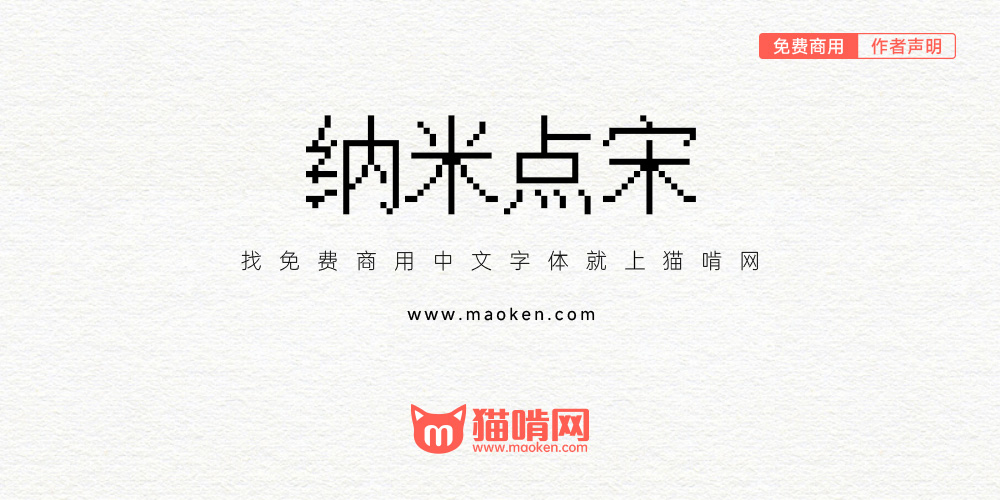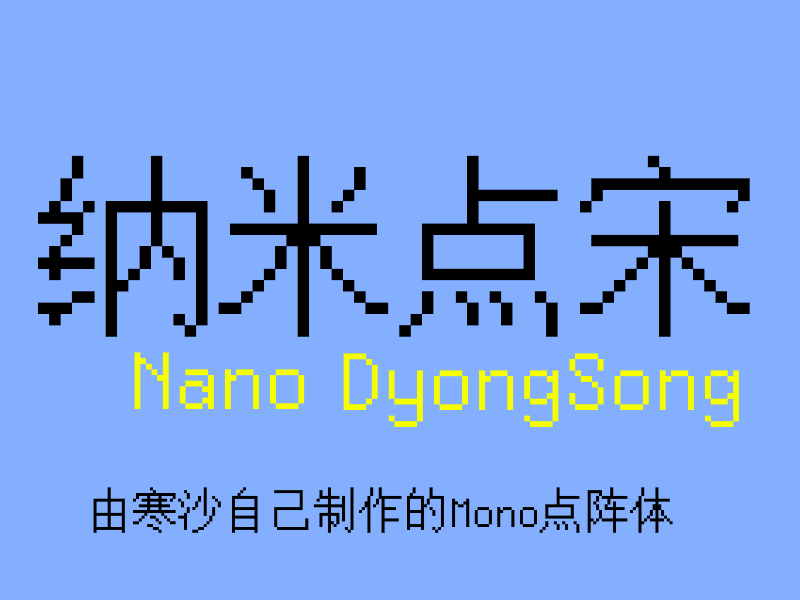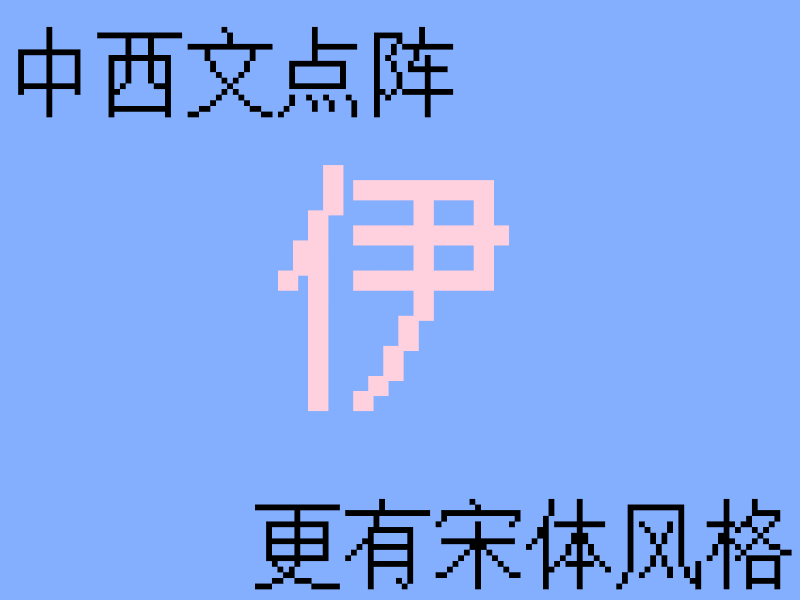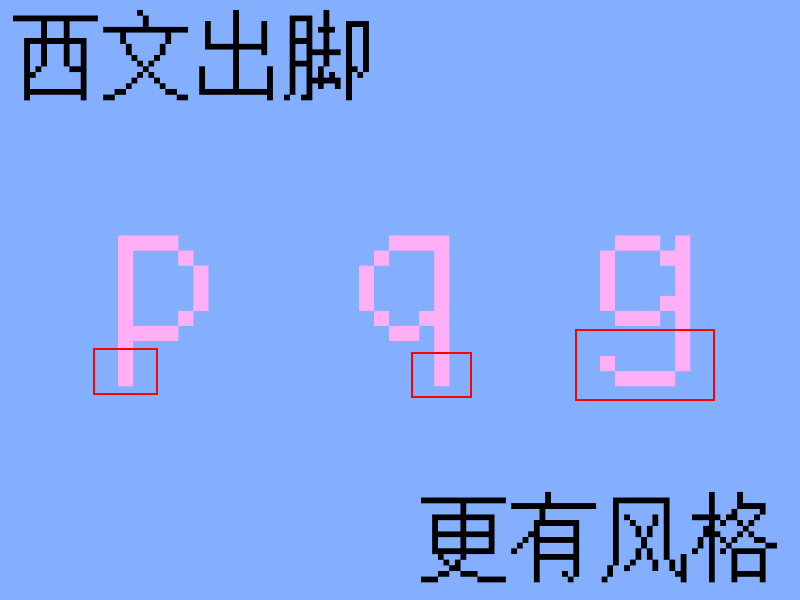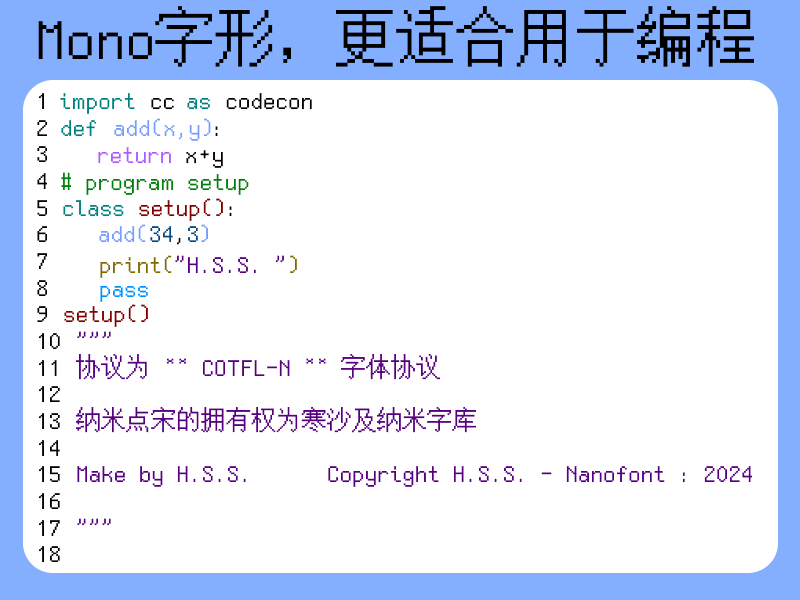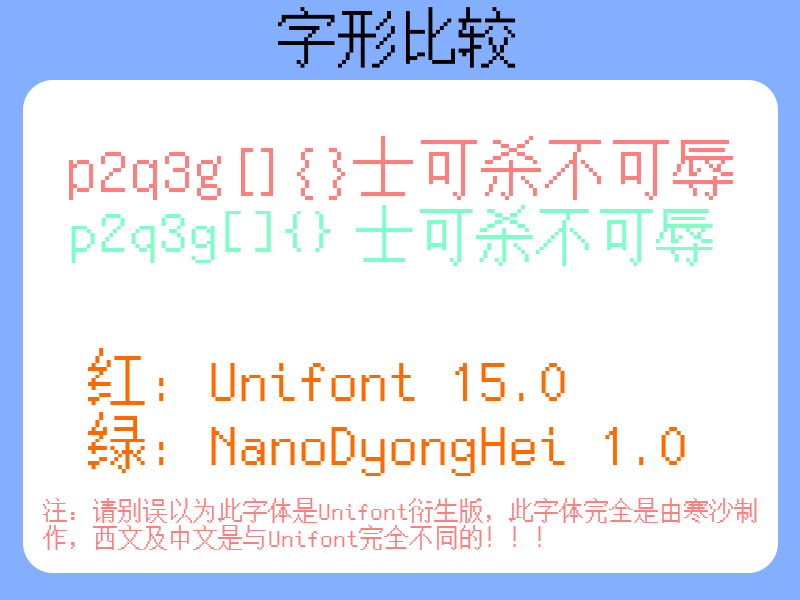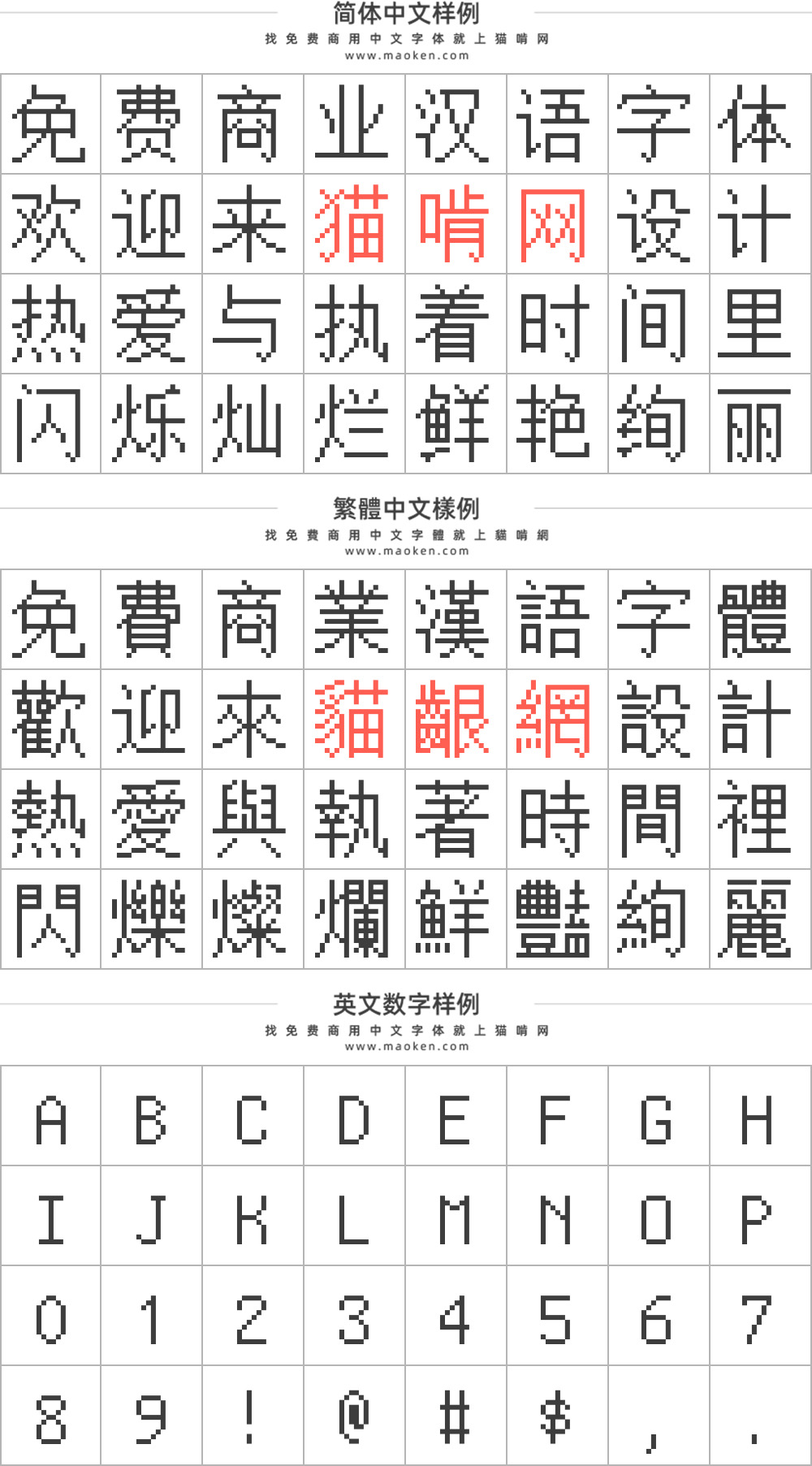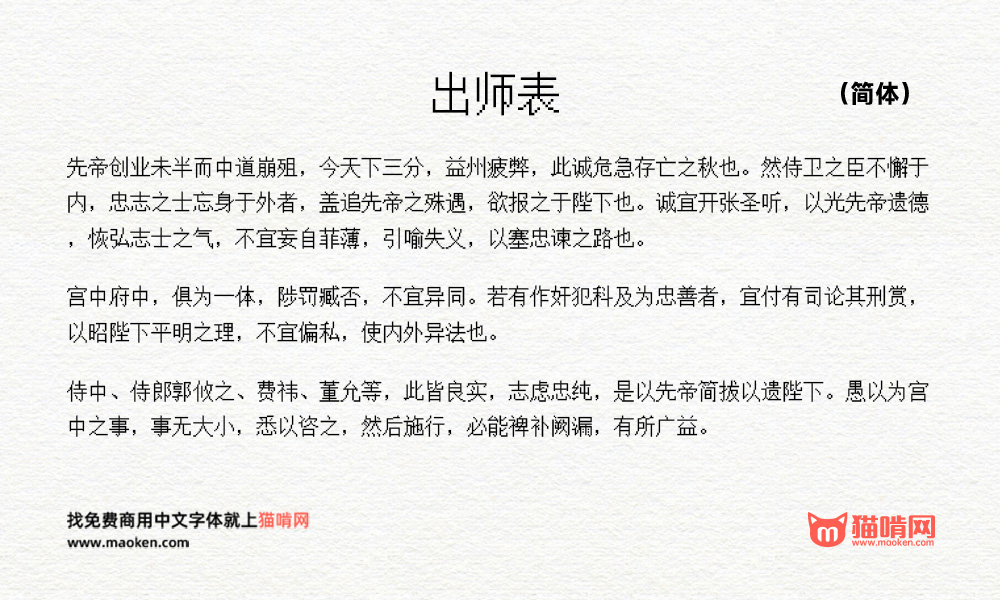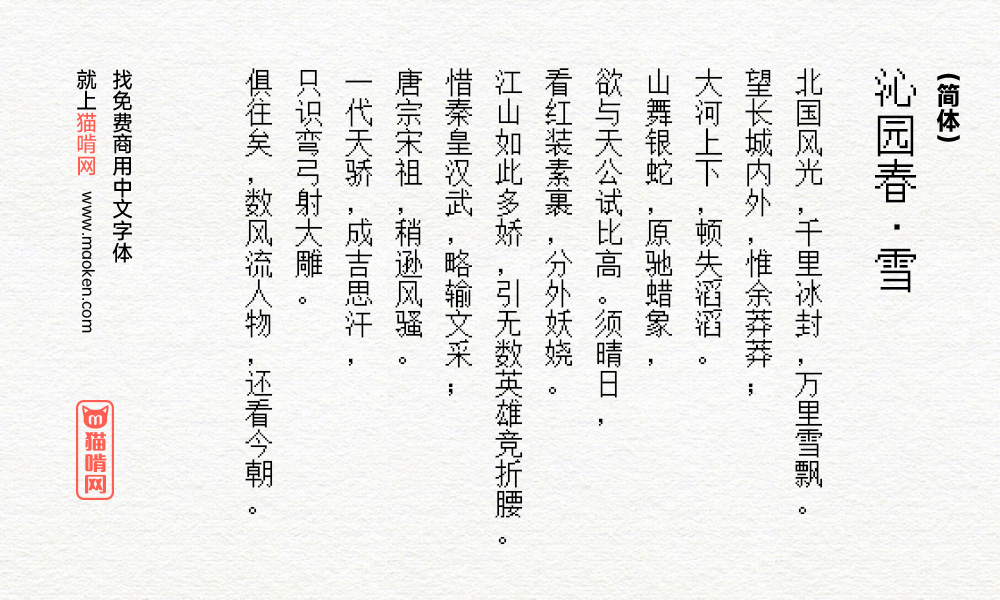
这是一款由寒沙自己制作的Mono点阵体(并不是Unifont的衍生版) ,支持中文与西文,未来还会继续更新!!!
纳米点宋专有的Mono字形,能够更好适配于编程字体,有很好的易读感
字体制作有可能有一些误差,字符有可能会错误或制作不精良!
还有要说明一下,这个字体是由unifont改过来的,而unifont用的是ofl协议(其中一个),所以此字体也应使用
可能一部分参考了unifont字体,但人家不是基于unifont字体的
看到 GitHub 仓库目前无人问津,而且作者亲历亲为在猫啃网回复,那我就写在这里吧。有人质疑西文以外的部分与 Unifont 相同,作者回复“这是自己做的,当然不一样了”。这样的回复是不具有任何说服力的。本着实践检验真理的原则,我检查了了一下这个字体的字形,却发现了更严重的问题——这个字体除了极少部分英文字母外,其他部分似乎是从中易宋体 16 点阵薅过来的,单看丑陋无比的假名与全角希腊字母就可以很轻松地看出来。薅中易宋体的后果可要比 Unifont 严重多了。如果作者只是以之为参照,后续再慢慢改进的话,就不要把未完成的部分放出来。其实,中易宋体的点阵大部分用的是国标 GB5199 的字形,但在此基础上补了一些字符(如日语长音符)。绘制与(强制性)国标相同的字形本身是没有问题的(实际上 Unifont 也是基于国标字形的),但从中易宋体薅字形是有法律风险的,尤其是你把国标未提及的长音符也薅过来了。另外,通过“引流”“不可开源”之类的措辞可以看出,作者可能对自由/开源软件的运行机制并不了解,建议补充一下相关知识。另起炉灶编写字体授权也是非常不建议的,至少你目前编写的这个版本在有些措辞上很模糊,可能不具备法律效力。如确实有需求,建议参考 SIL 的全文来编写,而不是简化后的“您可以……您不可以……”这种。
UniFont的中文字形在新版中易宋体(Win7/10)被使用过。
其实“Unifont 的中文字形在新版中易宋体被使用过”这个关系是不准确的。它们的 16×15 点阵汉字字形均来源于 GB5199 国标,而这个国标本来是一个强制标准(后来改成推荐标准了),里面规定的字形属于公有领域,因此不存在这两个字体间谁使用谁的问题,即使字形看起来完全相同也没有侵权的风险。问题在于,中易宋体夹带了一些国标中未规定的私货(比如丑陋的日语的长音符),这部分字形应是中易宋体版权所有的,却被该字体原封不动搬了过来,这就存在法律风险了。顺便一提,Unifont 只是汉字部分使用了国标字形,其他部分(拉丁字母、西里尔字母、希腊字母、平假名片假名等)都是自制的,甚至还补了一些新的字符(如“鿫”),这是无可指摘的。
这字体不是基于unifont字体的,你们在这答非所问,干什么?
西文以外的部分看不出和 UniFont 有什么区别。
这是自己做的,当然不一样了